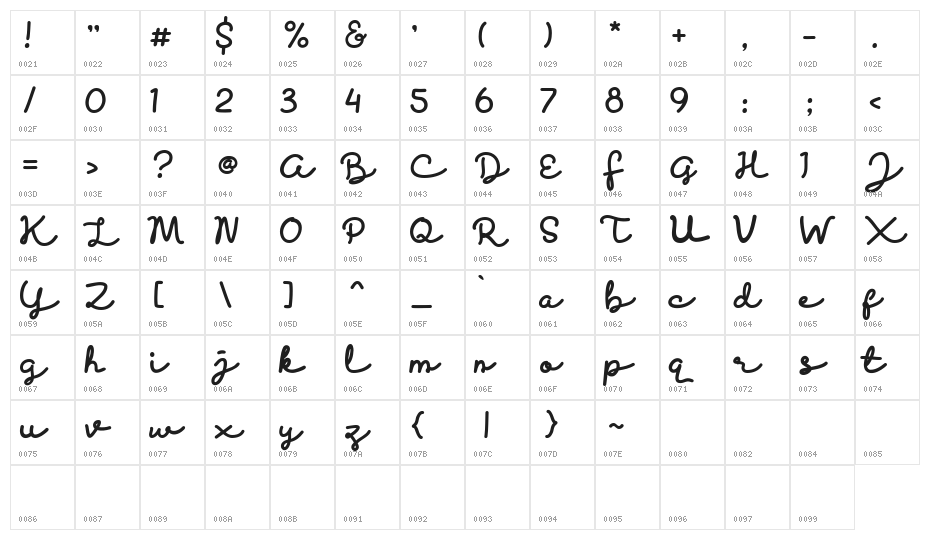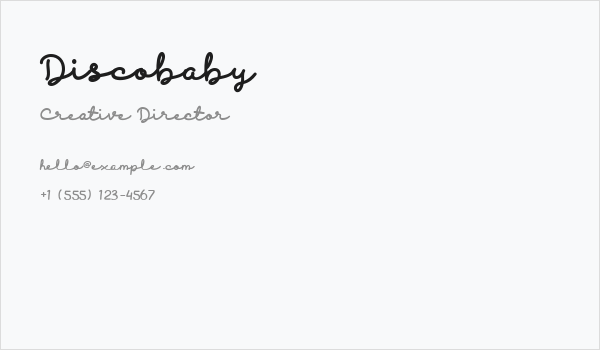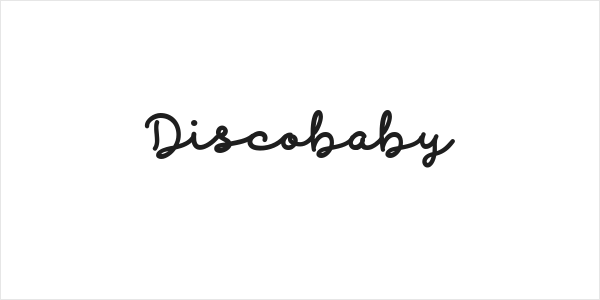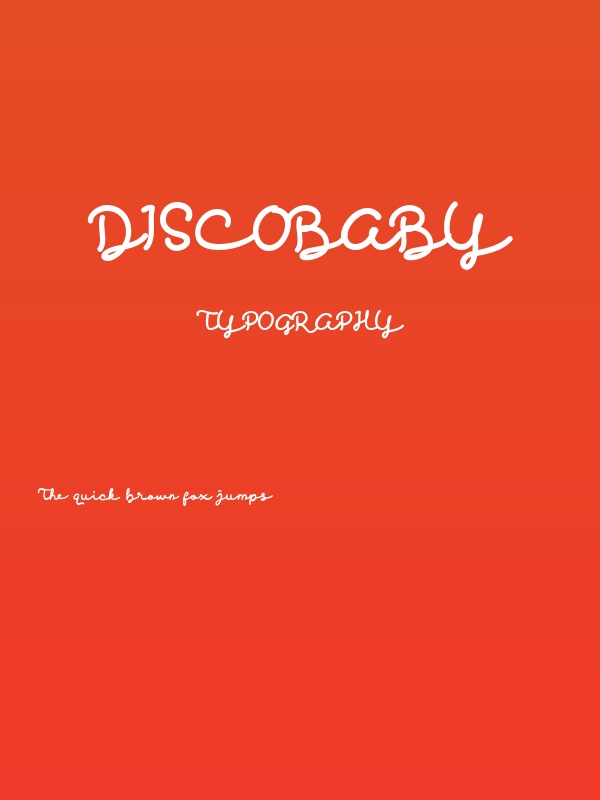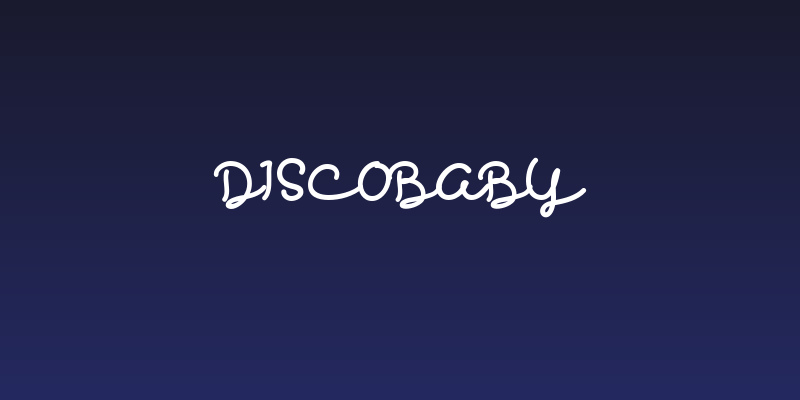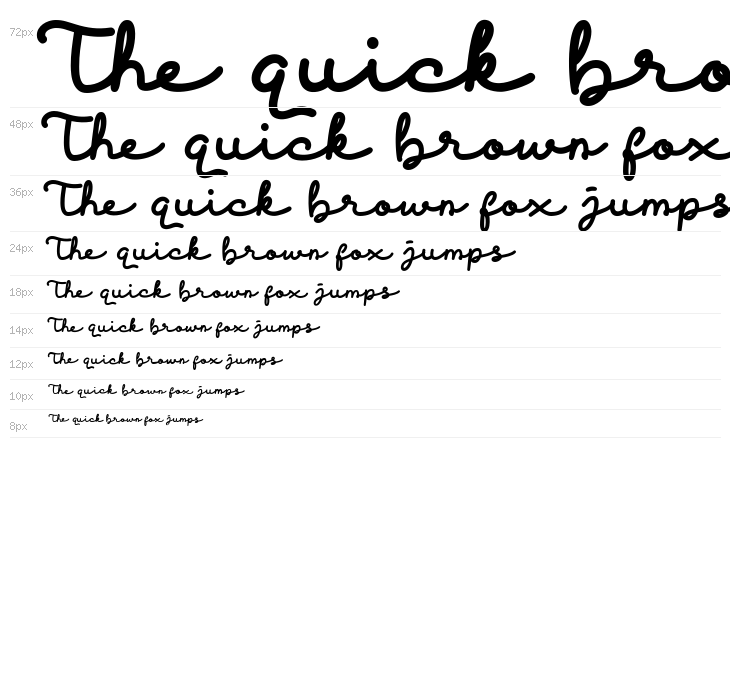
Discobaby Font
| Gesamtstil | Playful |
| Anwendungsfall | Logos, Headlines, Invitations |
| Vorgeschlagene Projekte | Perfect for greeting cards, children's book covers, playful branding, and social media graphics. |